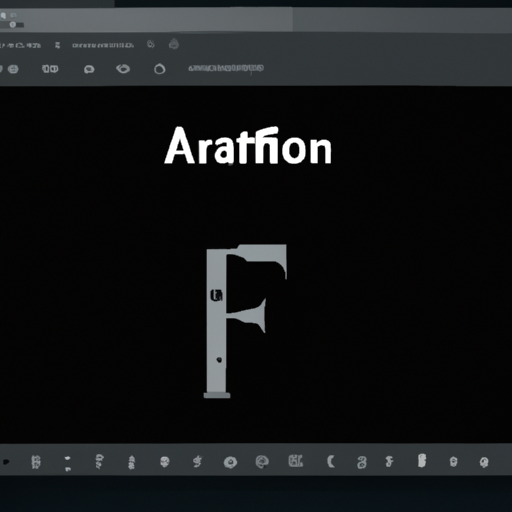
יסודות והיסטוריית הטיפוגרפיה
לטיפוגרפיה, אלמנט שמתעלמים ממנו לעתים קרובות בעיצוב, יש היסטוריה עשירה והיא ממלאת תפקיד מכריע בשיפור הקריאות וחווית המשתמש. פוסט זה בבלוג יעמיק ביסודות ובהיסטוריה של הטיפוגרפיה, החל מראשיתה ועד לשימוש עכשווי במדיה דיגיטלית.
מהי טיפוגרפיה?
טיפוגרפיה היא האומנות והטכניקה של סידור הכתב בצורה מושכת ויזואלית וניתנת לקריאה. זה כולל בחירה וסידור של גופנים, גדלים, מרווחים ואלמנטים עיצוביים אחרים כדי ליצור תקשורת מגובשת ויעילה. לטיפוגרפיה תפקיד מכריע בצורות שונות של מדיה חזותית, לרבות ספרים, עיתונים, פרסומות, אתרי אינטרנט ועוד. זהו עמוד השדרה של תקשורת כתובה ויכול להשפיע רבות על האופן שבו מידע מועבר ונתפס.
בבסיסה, טיפוגרפיה היא יותר מסתם בחירת גופנים וסידור טקסט. מדובר בהבנת העקרונות של קריאות, קריאות והיררכיה. קריאות מתייחסת לכמה קלות ניתן לזהות אותיות ותווים, בעוד שקריאות מתייחסת לכמה קלות ניתן להבין טקסט. היררכיה, לעומת זאת, עוסקת בארגון והדגשה של אלמנטים שונים בתוך הרכב. עקרונות אלו מנחים את הטיפוגרפים בקבלת החלטות לגבי בחירת גופנים, מרווחים, אורכי שורות וגורמים אחרים המשפיעים על הקריאות הכללית והמשיכה החזותית של הטקסט.
לטיפוגרפיה יש היסטוריה עשירה שתחילתה בימי קדם. זה התפתח מציורי מערות וכתובות פשוטים לפיתוח סוג מטלטלין בתקופת גוטנברג. עם המצאת הדפוס, הטיפוגרפיה הפכה לסטנדרטית ונגישה יותר, ואפשרה ייצור המוני של ספרים וחומרים מודפסים אחרים. עם הזמן הופיעו סגנונות ותנועות טיפוגרפיות שונות, המשקפות את ההתקדמות התרבותית והטכנולוגית של כל תקופה.
בעידן הדיגיטלי של היום, הטיפוגרפיה התרחבה מעבר למדיה המודפסת המסורתית. עם עליית האינטרנט והפלטפורמות הדיגיטליות, טיפוגרפיה הפכה למרכיב חיוני בעיצוב אתרים, ממשקי משתמש ויישומים ניידים. הופעת העיצוב הרספונסיבי אתגרה גם את הטיפוגרפים ליצור סוג שמסתגל בצורה חלקה במכשירים ובגדלים שונים של מסך.
איור המציג גופנים וגופנים שונים
מציורי מערות לסוג מטלטלין: שחר הטיפוגרפיה
ניתן לאתר את מקורות הטיפוגרפיה לצורות המוקדמות ביותר של תקשורת אנושית. לפני המצאת מערכות הכתיבה, אבותינו הסתמכו על ציורי מערות, סמלים ופיקטוגרפים כדי להעביר מסרים. צורות פרימיטיביות אלו של תקשורת חזותית הניחו את הבסיס לפיתוח הטיפוגרפיה כפי שאנו מכירים אותה כיום.
כאשר הציביליזציות החלו לפתח מערכות כתיבה, התברר הצורך בשיטות יעילות יותר לשעתוק טקסט. המצרים הקדמונים, למשל, השתמשו בהירוגליפים מגולפים באבן או כתובים על מגילות פפירוס. הסינים הקדמונים פיתחו טכניקות דיו ומברשת לכתיבת תווים על משי ונייר. מערכות הכתיבה המוקדמות הללו דרשו מיומנות וזמן עצומים להפקה, והגבילו את הפצת המידע.
נקודת המפנה בהיסטוריה של הטיפוגרפיה הגיעה עם המצאת הכתב המיטלטלי על ידי יוהנס גוטנברג במאה ה-15. טכניקה מהפכנית זו אפשרה ליצוק אותיות בודדות במתכת ולהרכיב אותן למילים ולמשפטים. ניתן לעשות שימוש חוזר בסוג הנייד ולשלב בתצורות שונות, מה שמאפשר ייצור המוני של חומרים מודפסים.
להמצאה של גוטנברג הייתה השפעה עמוקה על החברה. הוא סימן את תחילתה של מהפכת הדפוס וסלל את הדרך להפצת ידע בקנה מידה גדול בהרבה. ספרים, עלונים ועיתונים הפכו נגישים יותר לציבור הרחב, מה שהוביל להתפוצצות של אוריינות והפצת רעיונות.
הטיפוגרפיה המשיכה להתפתח ככל שהופיעו טכנולוגיות חדשות. כניסתה של הליטוגרפיה במאה ה-19 אפשרה שכפול של תמונות וטקסט ביתר קלות. מכונת הכתיבה, שהומצאה בסוף המאה ה-19, הביאה לעידן חדש של כתיבה מכנית. ועם הופעת המחשבים במאה ה-20, הטיפוגרפיה נכנסה לעידן הדיגיטלי, ואיפשרה למעצבים להתנסות במגוון רחב של גופנים, סגנונות ואפקטים.
השפעת בית הדפוס: נקודת מפנה?
המצאת בית הדפוס על ידי יוהנס גוטנברג במאה ה-15 חוללה מהפכה בעולם הטיפוגרפיה והייתה לה השפעה עמוקה על החברה כולה. עם היכולת לייצר ספרים וחומרים מודפסים אחרים בקצב מהיר הרבה יותר, הדפוס מילא תפקיד מרכזי בהפצת הידע ובהפצת הרעיונות.
לפני הדפוס הועתקו ספרים בקפידה בעבודת יד, תהליך מפרך וגוזל זמן. כתוצאה מכך, הספרים היו נדירים ויקרים, והגבילו את הגישה לחינוך ולמידע. בית הדפוס שינה זאת בכך שהפך ספרים לזמינים יותר וזמינים באופן נרחב יותר. זה הפך את הידע לדמוקרטי, ואפשר לחלוק רעיונות בין מדינות ויבשות.
גם לדפוס היה תפקיד משמעותי ברפורמציה הפרוטסטנטית. מרטין לותר, הנזיר והתיאולוג הגרמני, השתמש בדפוס כדי להפיץ את כתביו ורעיונותיו המאתגרים את הכנסייה הקתולית. זה הוביל להפצה נרחבת של יצירותיו של לותר, ועורר מהפכה דתית ברחבי אירופה. הדפוס העצים יחידים ואפשר חילופי רעיונות חופשיים, אתגר מוסדות מסורתיים וסלל את הדרך לתמורות אינטלקטואליות ותרבותיות.
יתר על כן, לדפוס הייתה השפעה עמוקה על השפה והאוריינות. הדפסה סטנדרטית הקלה על אנשים ללמוד לקרוא ולכתוב, מכיוון שהם יכלו כעת להתייחס לחומרים מודפסים עם איות ודקדוק עקביים. זה הוביל לעלייה בשיעורי האוריינות והתפתחותן של שפות לאומיות. זה גם תרם לסטנדרטיזציה של הטיפוגרפיה, עם הקמת גופנים ספציפיים ומוסכמות טיפוגרפיות.
תמונה של בית הדפוס של גוטנברג
בית הדפוס של גוטנברג
"האם טיפוגרפיה משפיעה על תפיסה?": הפסיכולוגיה של הטיפוגרפיה
טיפוגרפיה היא לא רק בחירת גופנים וסידור טקסט בדף; יש לה גם השפעה עמוקה על האופן שבו אנו תופסים ומפרשים מידע. הפסיכולוגיה של הטיפוגרפיה חוקרת כיצד אלמנטים טיפוגרפיים שונים יכולים להשפיע על הרגשות, המחשבות וההתנהגויות שלנו.